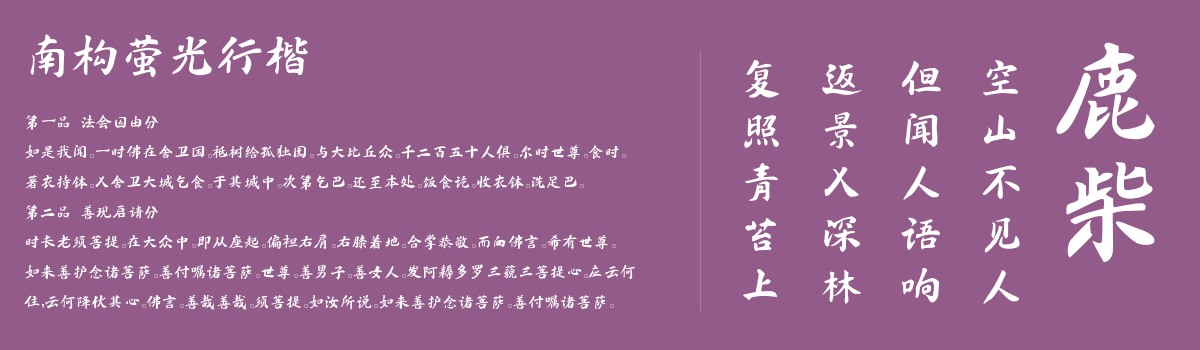
南构萤光行楷
南构萤光行楷是一款艺术字体,这款行楷字体,笔画兼具楷书规整与行书灵动。横画带微弧,不僵直;竖画挺拔含弹性,如竹节蓄力。撇捺舒展有度,收笔轻扬似流萤振翅;转折圆融过渡,无生硬棱角。结构疏密匀停,部件穿插自然,重心沉稳却不失活泼。整体线条温润通透,似月光下的萤火,既有楷书端庄骨力,又有行书飘逸动感,刚柔相济,灵动不潦草。适合用于一些广告标题、平面文案、海报标题、网页广告用字的编辑。